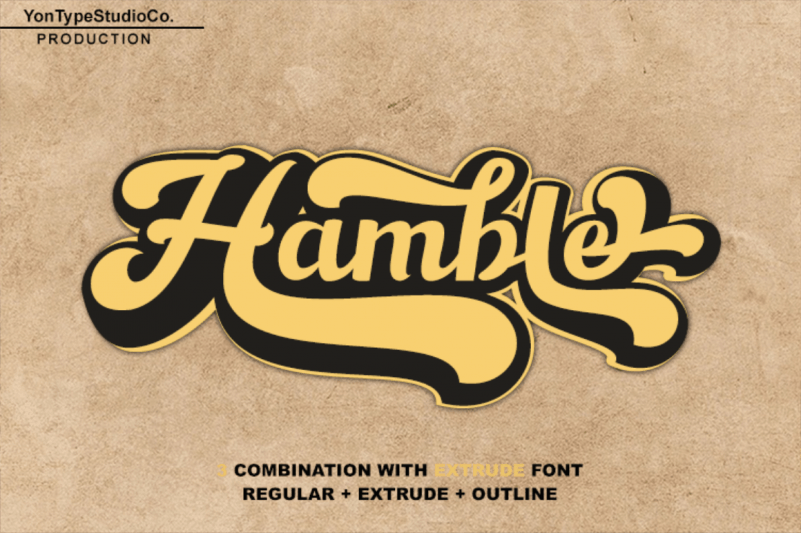
Hamble Bold Script Font – Download Grátis
A Hamble Bold Script é uma tipografia bold e elegante que evoca os designs tipográficos dos anos 70. Inspirada nessas criações icônicas, essa fonte oferece três estilos combináveis perfeitos para logotipos, placas de sinais ou pequenos cartazes comuns. Ela vem rica em opções alternativas que contam com mais de cem caracteres Unicode PUA, garantindo uma variedade incrível e dinâmica. Esses recursos adicionais permitem que você desenvolva designs gráficos marcantes, fortes e artísticas para aplicativos como fitas, panfletos, bandanas publicitárias, capas de livros, títulos ou até mesmo fontes clássicas. A Hamble Bold Script está destinada a multi-línguas, oferecendo suporte para uma ampla variedade de idiomas. Para acessar essas alternativas de caracteres, é necessário um software que suporta recursos OpenType como Adobe Illustrator CS, Adobe Photoshop CC, Adobe Indesign e Corel Draw. Esta fonte não apenas complementará suas criações digitais, mas também dará vida a sua arte física em materiais impressos, tornando-a uma opção indispensável para designers gráficos que desejam explorar novas maneiras de criar design.